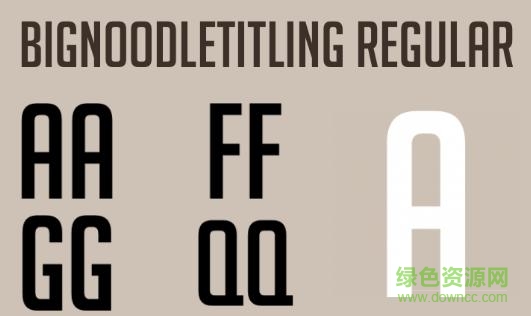
bignoodletitling
bignoodletitling字體是一款極具特色的英文創(chuàng)意字體,字母大小設(shè)計(jì)不一,個(gè)性色彩強(qiáng)烈,綠色資源網(wǎng)還有很多和bignoodletitling差不多的中文字體供你下載,需要的朋友快來收藏吧!
bignoodletitling